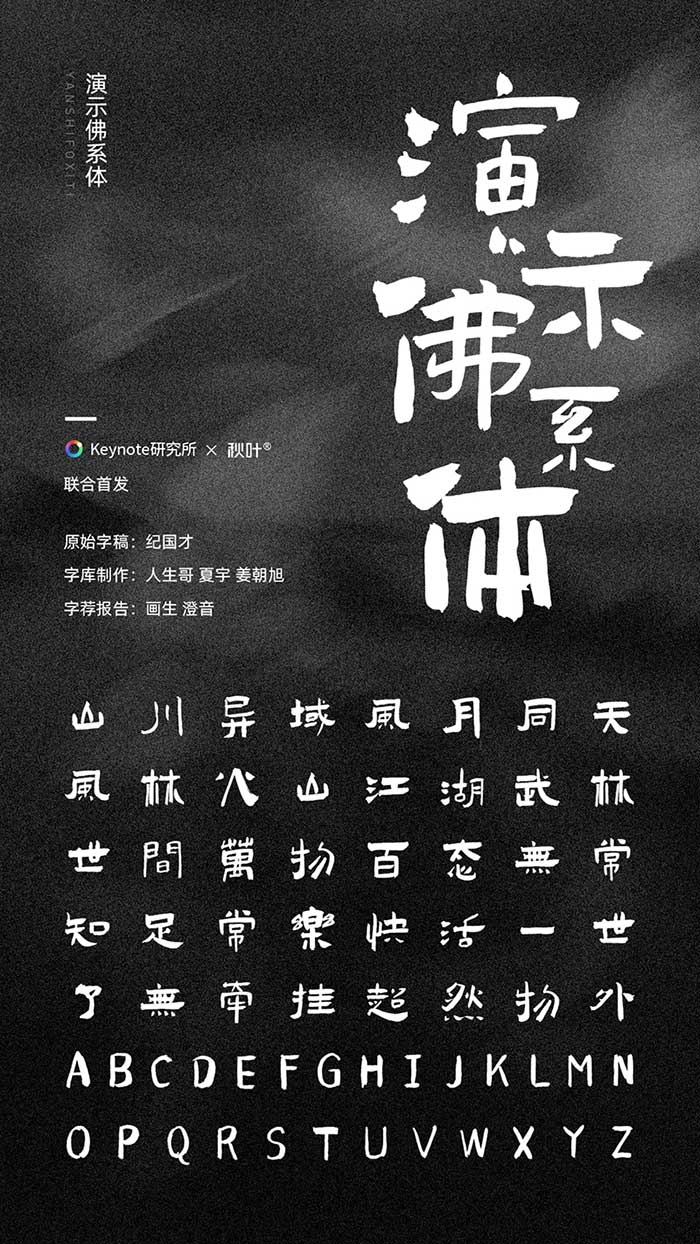
演示佛系體由酷愛書法的紀國才老先生,在80歲這年親手寫了一套獨具風格的字體,並授權 Keynote研究所 和 秋葉PPT 面向全社會聯合首發,全渠道免費商用!
紀國才老先生一生經歷了風雲更迭,字如其人,印刻著時光的痕跡,沉澱著歲月的厚重,也訴說著人生的灑脫,有種超然物外之態。
演示佛系體打破固有造字框架的條條框框,又有一致的內核,形散而神不散;演示佛系體不再是常規書法字體中怒放的飛白和筆觸,將瀟灑收斂,但也厚重有力;字體整體乍看之下,似以繁體字為主,但多看一些,才發現,諸多奇特的偏旁部首寫法,是現代簡體繁體都不具備的。